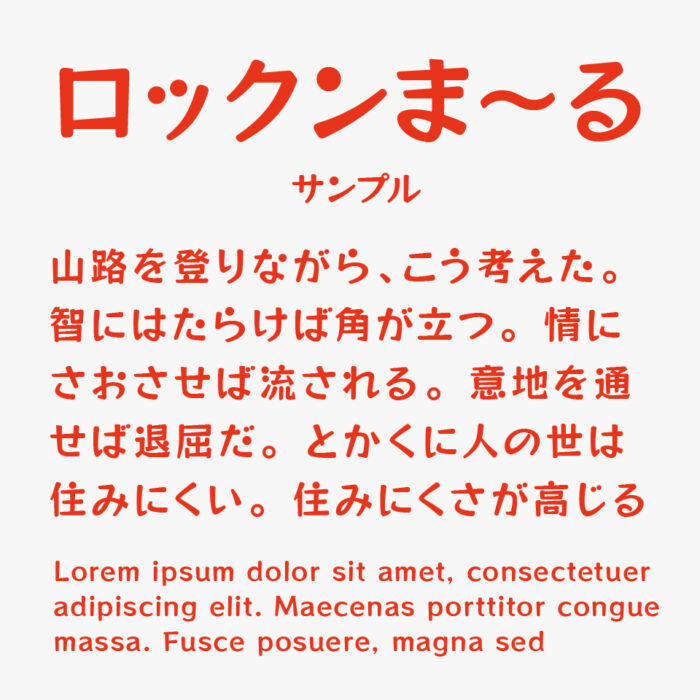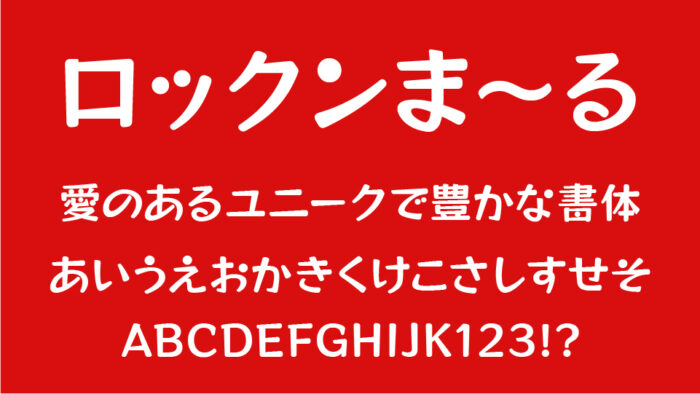
ロックンま~るフォントは、ロックンロールone(RocknRoll One)フォントをベースに角丸加工して制作されたフォントです。
元のロックンロールone(RocknRoll One)のトゲっぽい雰囲気から、まろやかで遊び心のあるシルエットになり、親しみやすく可愛らしい丸文字フォントとなっています。文字に散らばっている丸のシェイプはそのまま継承されているので、読んでいて楽しくなるようなそんな雰囲気があるフォントです。